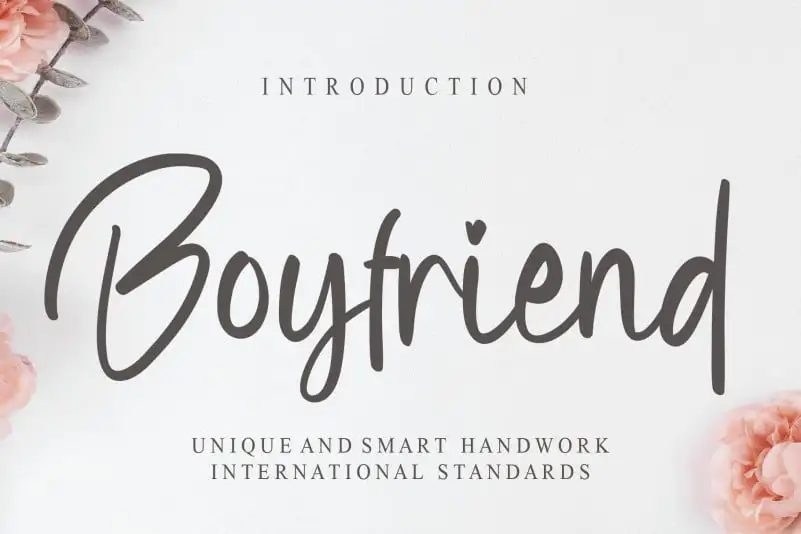
Boyfriend Script Font – Download Grátis
Aqui está uma descrição embasada na sua instrução: Descubra uma nova experiência visual com a “Boyfriend Script Font” do designer creativeletter. Esta fonte, classificada como handwritten, é perfeita para quem busca um ar de personalidade e autenticidade em suas criações digitais. Com traços fluidos e escrita delicada que remetem ao estilo informal do cotidiano dos relacionamentos mais íntimos, a “Boyfriend Script Font” oferece uma experiência única na categoria de fontes handwritten. Seu charme casual irá transformar seu design, criando um ar elegante e descontraído para qualquer projeto. Combinada com outros recursos gráficos da marca creativeletter, essa fonte se destaca como a escolha perfeita para projetos que exigem uma certa dose de personalidade. Perfect para carregar em sua pasta de recursos, esta fonte vai te ajudar a destacar seu trabalho no universo digital. Seja você um designer ou um criador de conteúdo, a “Boyfriend Script Font” é o acessório perfeito para tornar suas criações ainda mais únicas e memoráveis.